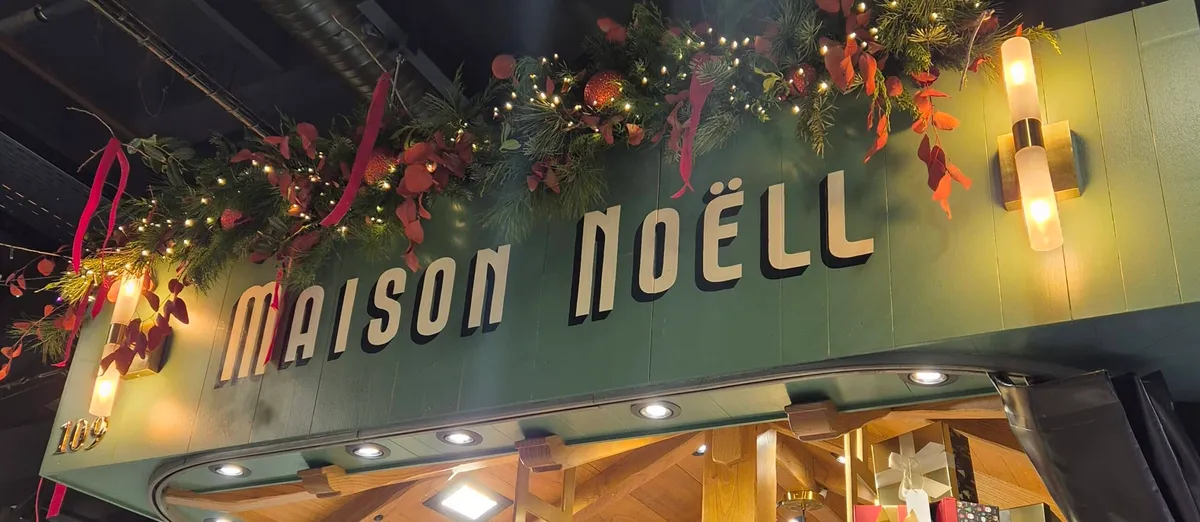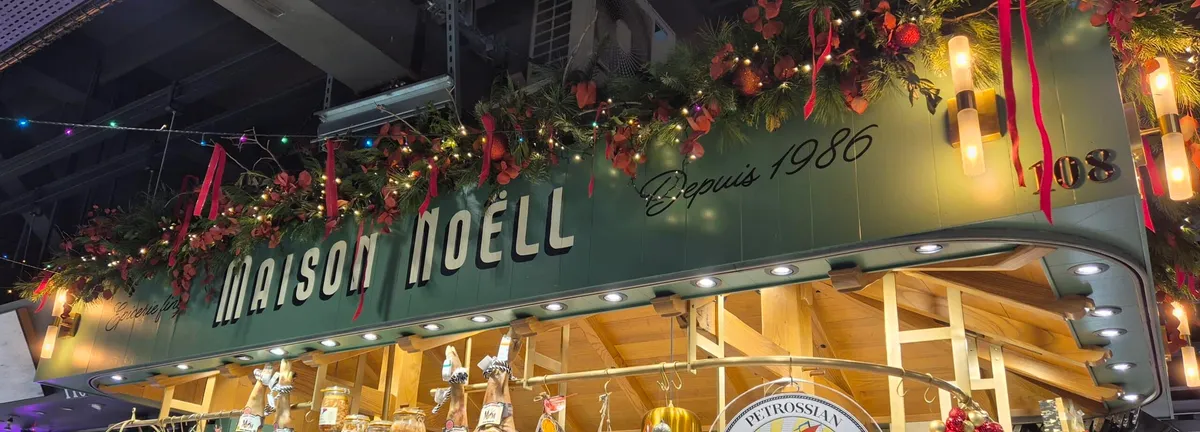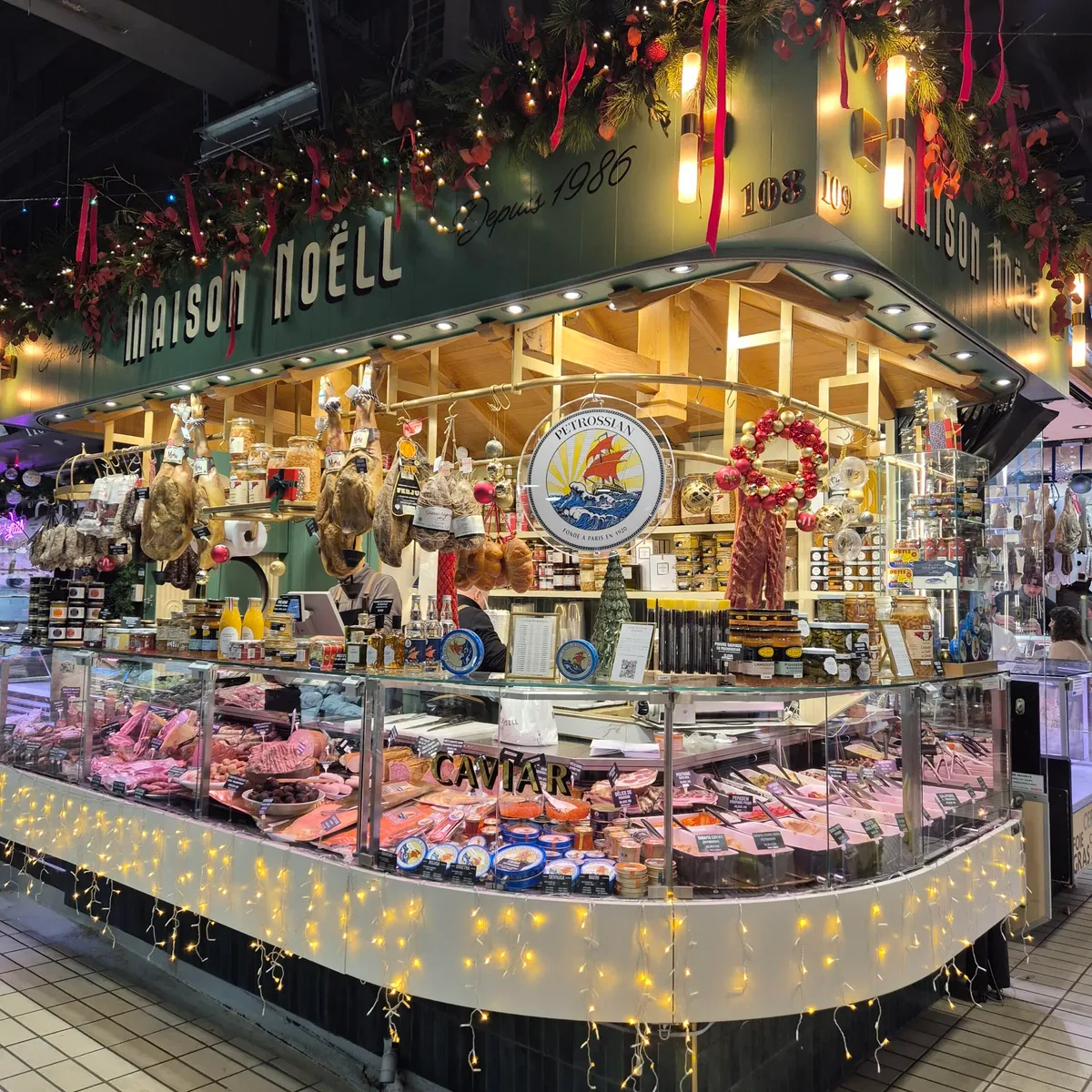
Maison Noëll – Marché Victor Hugo
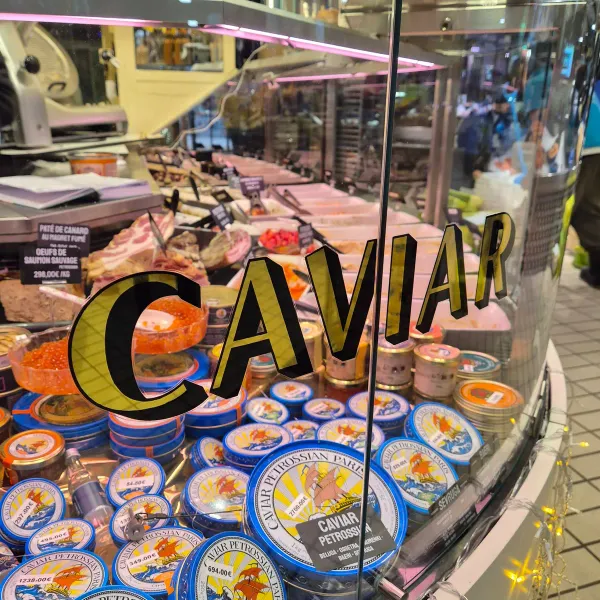
Création visuelle et peinture de 2 enseignes et une vitrine à la feuille d'or. Lettrage effet miroir en feuille d'or caviar sur la vitrine réfrigérée.
Maison Noëll